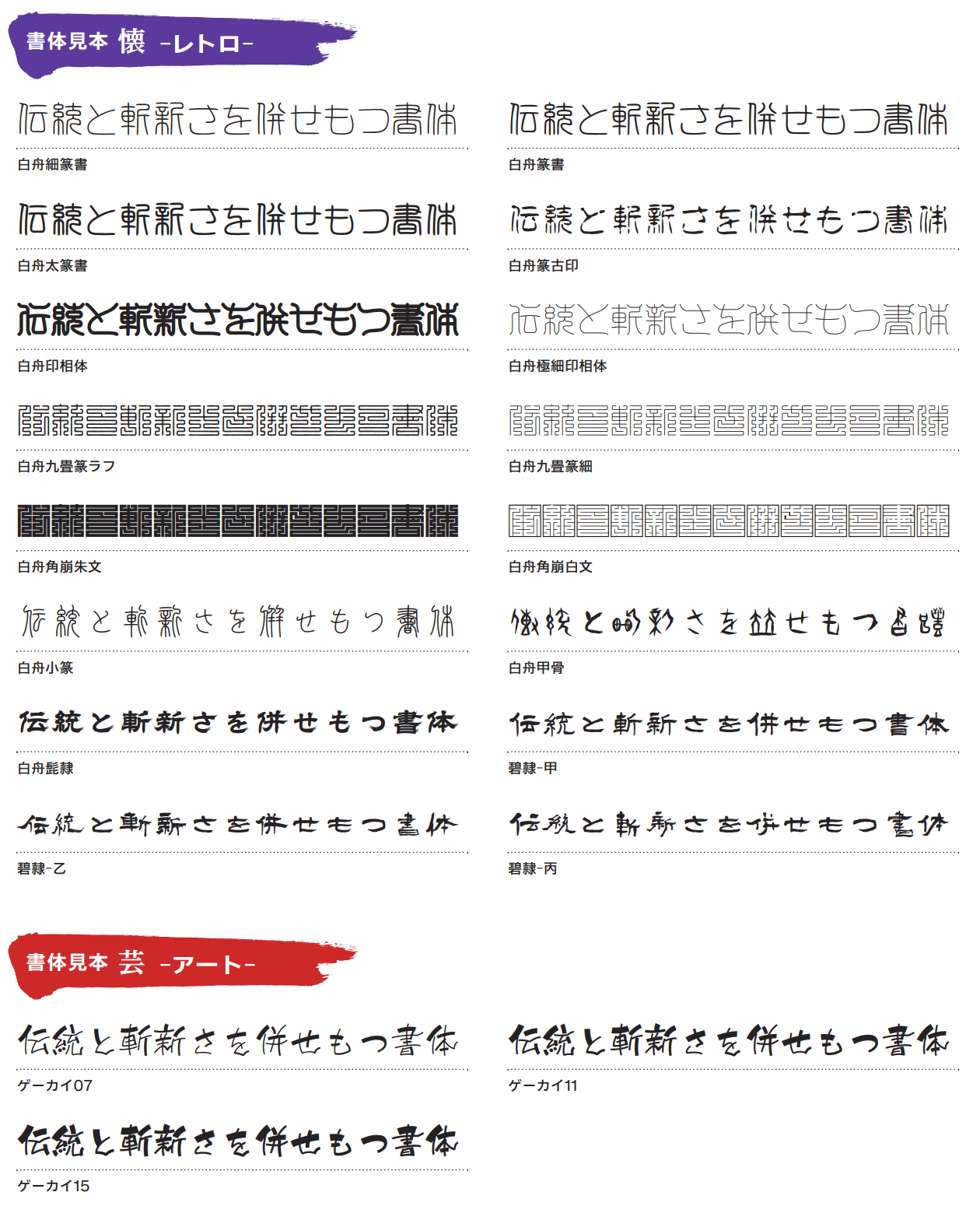
伝統的な書体からデザイン筆文字まで個性豊かな文字が揃う白舟書体と、看板の揮毫から生まれた毛筆書体で日本語の文字表現を豊かにする昭和書体。日本国内の2大筆文字フォントメーカーが生み出した筆文字フォントのサブスクサービス「J-Font.com (ジェイフォントドットコム)」をご紹介します。
白舟書体は、老舗の印章店が持つ伝統的書体から遊び心溢れるデザイン筆文字のフォントまで67書体以上を取り揃え、個性的かつ多彩な表現が持ち味のロングセラーブランド。昭和書体は、揮毫職人が一文字一文字丁寧に書き上げた本格筆文字72書体以上が揃い、超人気アニメ・コミックで採用されたことでも注目されています。
白舟書体の紹介
多くのTV番組や商品パッケージなどに多用されている大人気の遊び心溢れるデザイン筆文字や、本格的な印章にも使用される格調ある伝統書体がずらりとそろった白舟書体。
気軽に作るメニューやチラシ、和を感じる商品パッケージ、インパクトを与える映像テロップなど、プロ御用達のデザイン筆文字はさまざまな制作物で活躍します。
昭和書体の紹介
あらゆる使用目的にマッチする毛筆書体の提供を目指し、揮毫職人が1文字1文字丁寧に書き上げた本格毛筆書体ブランドです。
1950年頃から広告媒体製造業としての取組みを起源とし、2006年に毛筆フォント制作会社としてコーエーサインワークスを設立。2013年の組織変更を経て株式会社昭和書体に社名変更されました。直筆と見間違えるようなPC用毛筆書体制作にこだわりを持って、自社内ですべての制作業務を行い、和文毛筆という文化の継承に取り組んでいます。